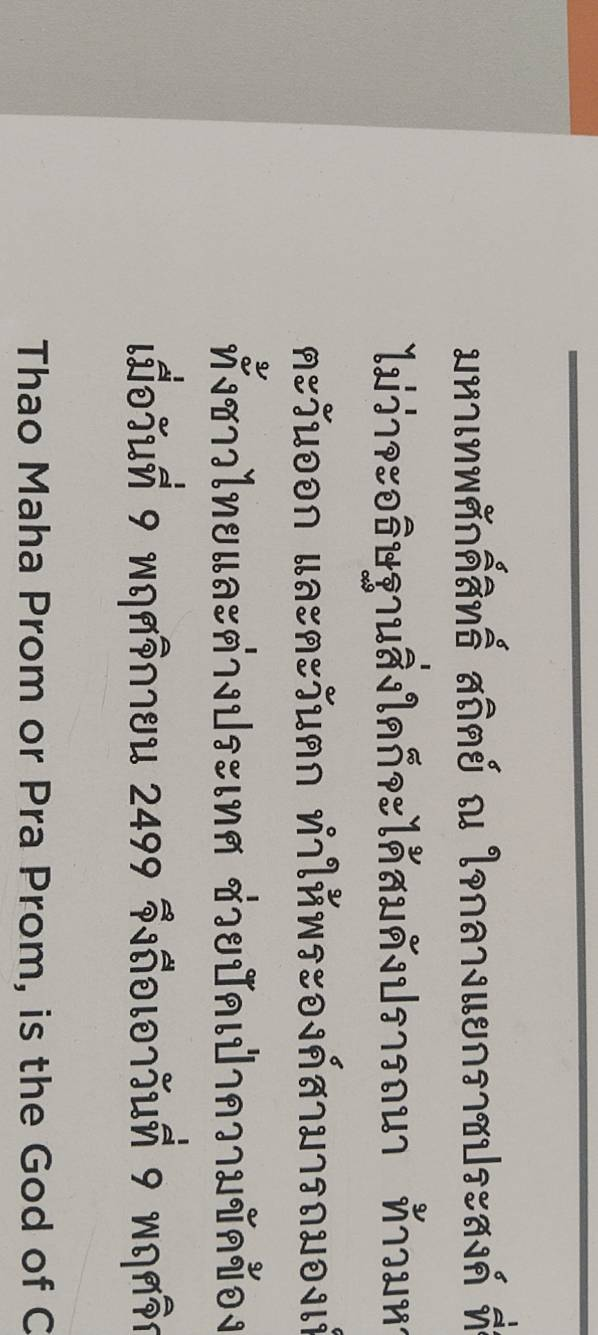
สอบถามชื่อฟอนต์ และวิธีดาวน์โหลด ถ้ามี
สวัสดีครับ พอดีไปเจอฟอนต์นี้ที่ดูคุ้นตามาก แต่ไม่แน่ใจว่ามันชื่อฟอนต์ว่าอะไร แต่จากที่ดูและจำได้คือ ฟอนต์น่าจะใช้ตัวหนา มีทั้งภาษาไทยและภาษาอังกฤษ และมันอยู่ในหนังสือเรียน โลก ดาราศาสตร์ และอวกาศ ฝากใครที่พอทราบชื่ฟอนต์ด้วยนะครับ ส่วนตัวอยากลองใช้ฟอนต์นี้ดู ไม่นับภาษาอังกฤษที่ดูบรรทัดด้านล่างนะครับ